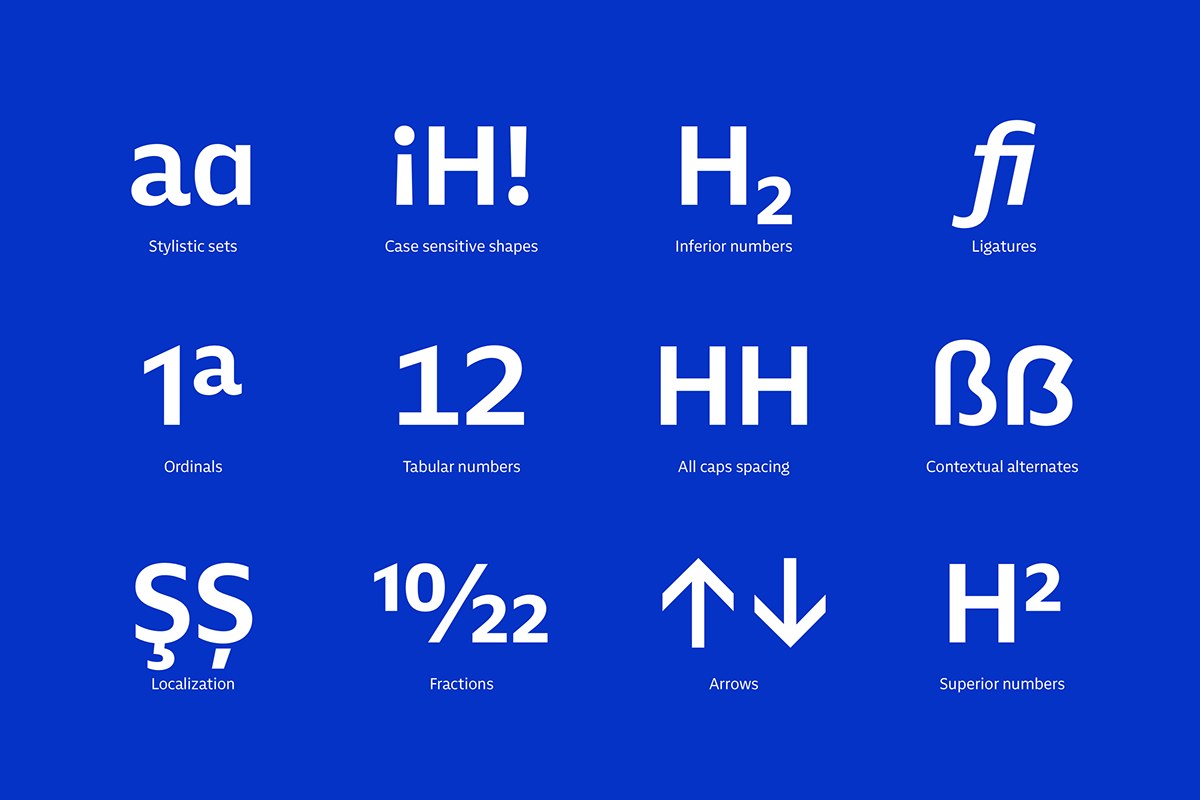
Nylo Typefamily
Nylo — Un sans humaniste contemporain. Lorsque j’ai fait mes premiers pas en tant que graphiste, les polices humanistes sans empattement faisaient fureur. Ils étaient partout. Comme s’il n’y avait pas d’autres polices. Quelques années plus tard, ils ont complètement disparu de mon radar – jusqu’à la conception de Nylo. La famille est un hommage à mon époque en tant que jeune designer et essaie en même temps de donner à ce genre impressionnant l’attention qu’il mérite.